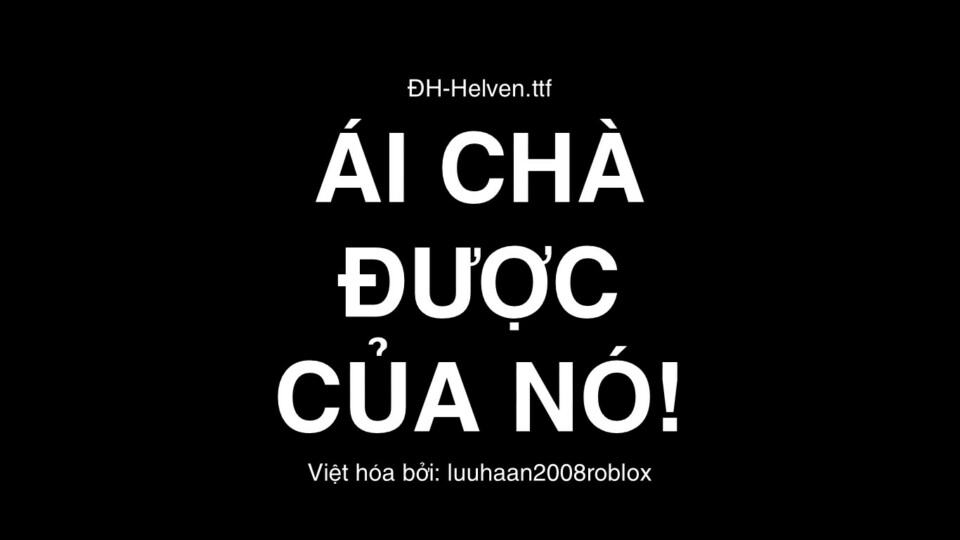
Font việt Hóa ĐH-Helven
Giới thiệu về bộ Font việt Hóa ĐH-Helven chuyên nghiệp
Trong lĩnh vực thiết kế đồ họa và soạn thảo văn bản tại Việt Nam, việc tìm kiếm một bộ font vừa hiện đại vừa hỗ trợ đầy đủ tiếng Việt là điều vô cùng quan trọng. Font việt Hóa ĐH-Helven nổi lên như một sự lựa chọn hàng đầu dành cho các nhà thiết kế và cộng đồng học thuật. Đây là phiên bản được tinh chỉnh kỹ lưỡng từ bộ mã gốc để tương thích hoàn hảo với bảng mã Unicode, giúp người dùng không còn lo lắng về lỗi hiển thị dấu câu hay các ký tự đặc biệt trong tiếng Việt. Khi sử dụng Font Miễn Phí này, bạn sẽ nhận thấy sự khác biệt rõ rệt về độ sắc nét và tính thẩm mỹ cao. Font việt Hóa ĐH-Helven sở hữu các đường nét dứt khoát, gọn gàng nhưng không kém phần mềm mại, tạo nên một tổng thể hài hòa cho mọi loại văn bản từ trình chiếu đến in ấn báo cáo.
Đặc điểm nổi bật của Font việt Hóa ĐH-Helven trong trình bày
Cấu trúc chữ hiện đại và dễ đọc
Lý do khiến Font việt Hóa ĐH-Helven được yêu thích chính là cấu trúc hình học cân đối. Các ký tự được thiết kế với độ rộng vừa phải, khoảng cách giữa các chữ cái (kerning) được tối ưu hóa để đảm bảo khả năng đọc tốt nhất trên cả màn hình máy tính và trên giấy. Đối với các bạn học sinh và sinh viên, việc sử dụng font chữ này trong các bài tiểu luận hay đồ án sẽ giúp nội dung trở nên chuyên nghiệp, thanh thoát và dễ tiếp cận hơn đối với người xem.
Tính ứng dụng đa dạng trong học đường
Không chỉ dừng lại ở các văn bản hành chính, Font việt Hóa ĐH-Helven còn cực kỳ phù hợp để làm tiêu đề cho các ấn phẩm truyền thông trường học. Bạn có thể dùng nó để thiết kế poster sự kiện, làm slide thuyết giảng cho giáo viên hoặc tạo ra những mẫu thiệp mời đầy sáng tạo. Nhờ bộ ký tự tiếng Việt chuẩn xác, mỗi con chữ đều toát lên sự chỉn chu và tôn trọng ngôn ngữ dân tộc, giúp thông điệp truyền tải đi xa và ấn tượng hơn trong mắt thầy cô và bạn bè.
Lưu ý khi phối hợp font chữ
Khi sử dụng Font việt Hóa ĐH-Helven, bạn nên kết hợp với các font chữ có chân (Serif) cho phần nội dung dài để tạo sự tương phản rõ rệt. Sự kết hợp này không chỉ giúp trang giấy có chiều sâu mà còn hướng sự chú ý của người đọc vào những đề mục quan trọng. Hãy tận dụng các định dạng in đậm và in nghiêng của bộ font này để nhấn mạnh các từ khóa chính, giúp bài viết của bạn có cấu trúc mạch lạc và khoa học hơn bao giờ hết.
Kết luận về bộ Font việt Hóa ĐH-Helven cho người dùng